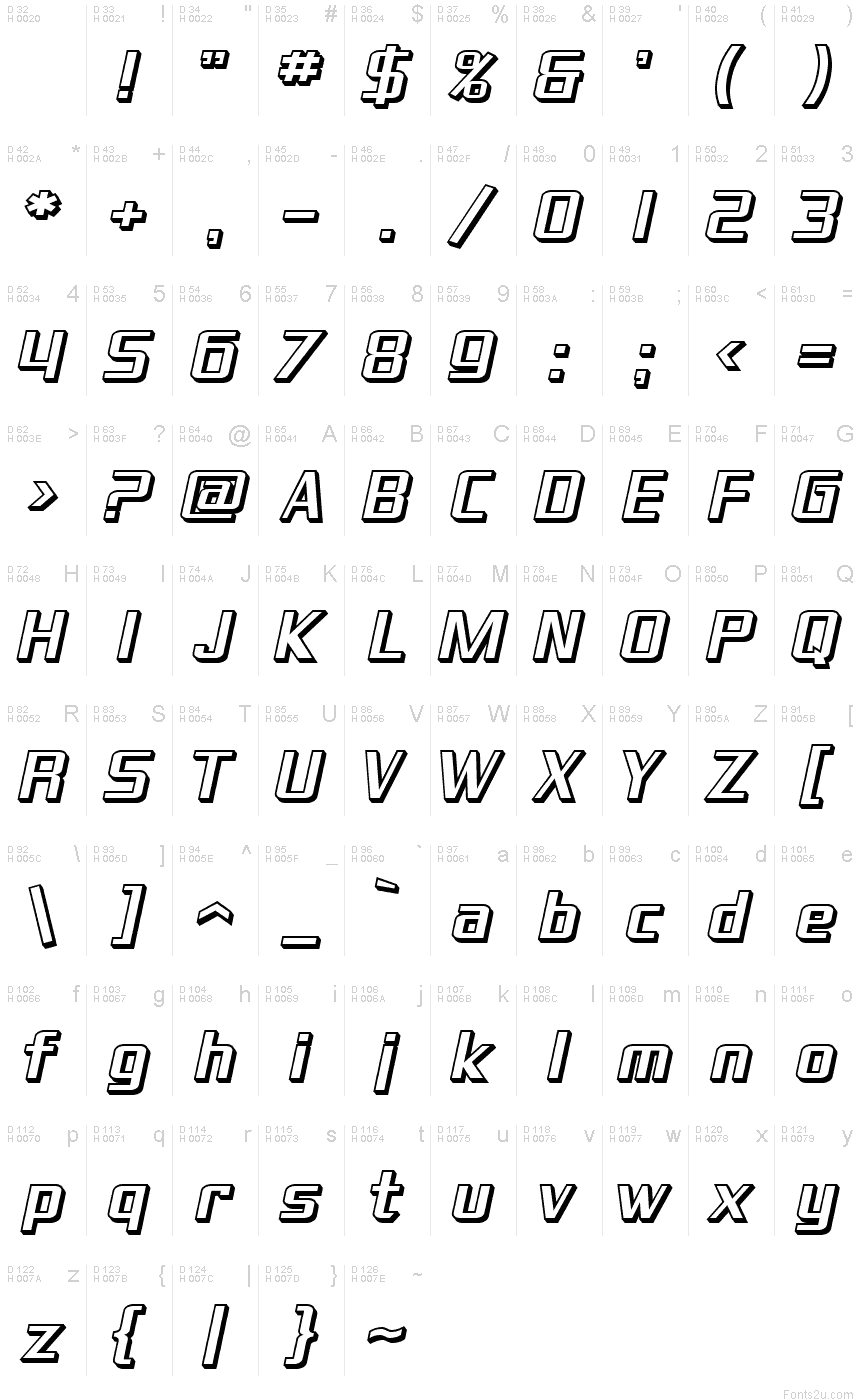
SF Theramin Gothic Shaded Oblique di ShyFonts Type Foundry è un font display techno gratuito, obliquo e ombreggiato, che richiama il ritmo arcade della fine degli anni '90. Le lettere sono fortemente inclinate verso destra, tagliate in forme ampie e angolari, e presentano un'ombra sfalsata e decisa che conferisce al design un aspetto dinamico, quasi di plastica stampata, piuttosto che puramente industriale.
È ideale per loghi di videogiochi, poster sci-fi, flyer di club, titoli e copertine che richiedono un font capace di trasmettere movimento intrinseco. Usalo quando vuoi che parole brevi, iniziali o intestazioni di brand sembrino proiettate in avanti: l'inclinazione e l'ombra pesante fanno tutto il lavoro, ancor prima di aggiungere colori o effetti grafici.